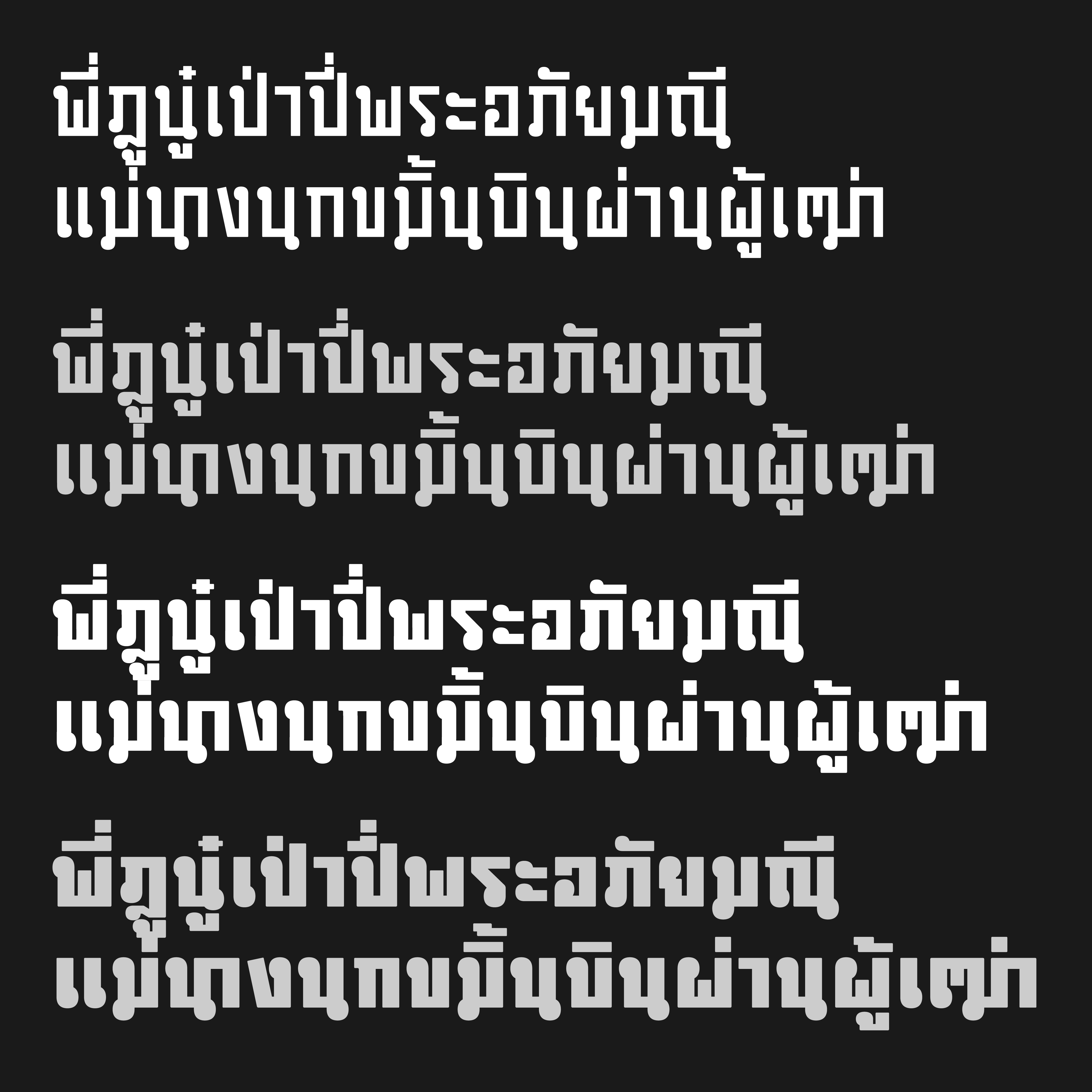
ขมิ้น | KAMINN
เอาไว้ทำป้ายสวนผลไม้ แปลงเกษตรสาธิต น้ำตก อุทยาน อะไรพวกนี้ ????
เหมือนโรงหนังเก่าด้วยครับ :12:
ต้นแบบฟอนต์ จากปก LP แม่นางนกขมิ้น - สมยศ ทัศนพันธ์
ขอพิมพ์เช็กระยะอีกรอบ เดี๋ยวมาต่อคิวฮะ
รู้สึกมันไม่ค่อยพอดีไงไม่รู้
อาจจะช่องไฟห่างไปนิดนึงใช่ไหมครับ จังหวะรสชาติมันเลยเปลี่ยนไป
อย่างสระ ะ ไม่แน่ใจว่าหดสั้นแล้วจะเนียนขึ้นไหม
มีเม็ดกลมๆนี่ ท่ายากเลย..
ช่องไฟตัวหนา นี่ดู ok หมดแล้วนะครับ แต่ตัวบาง ความรู้สึกห่างไปกระจิ๊ดนึงที่ แม่,นก ส่วน เป่า,ผ่าน นี่ไม่รู้สึกว่าห่าง แค่ต่างจาก นาง,เฒ่า
ชื่อฟอนต์ : ขมิ้น | KAMINN
ขมิ้น | KAMINN
ชุดฟอนต์พาดหัว เก่า และเก๋าโดดเด้ง
แรงบันดาลสุดหัวใจ จาก ปก LP แม่นางนกขมิ้น
ของ คุณสมยศ ทัศนพันธ์ ศิลปินเพลงไทยลูกทุ่ง
รางวัลแผ่นเสียงทองคำพระราชทาน จากบทเพลง "ช่อทิพย์รวงทอง"
พิเศษ !! ชุดฟอนต์ KAMINN ERODED
ทำมาเก่าเป็นพิเศษ พร้อมให้ใช้งานได้ทันที
เพิ่มความพิเศษด้วย OpenType Features ต่าง ๆ
ไม่ว่าจะเป็นการจัดการสระ / วรรณยุกต์ไทย ด้วย Anchor Marking,
Ligatures, การทำ Kerning เพื่อความสวยงาม
ชุดฟอนต์ "ขมิ้น"